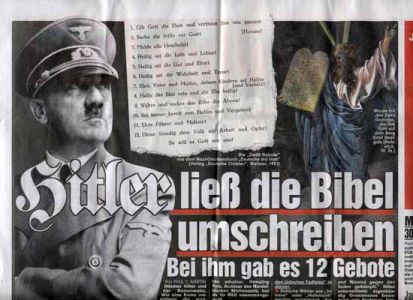
Hitler lügt wie gedruckt
Von wegen Schaftstiefelgrotesk – der Führer steht doch mehr auf Schwabacher Judenlettern, jedenfalls, wenn man der heutigen BILD glauben mag.
Ich finde diesen Deinen Beitrag eher fehl am Platze und überflüssig.
Solche (BILD-Zeitungs-)Beiträge ignoriert man, aber man wertet sie nicht auf, indem man sie zusätzlich irgendwo publiziert. Darüber hinaus sollte man solche antisemitischen Begriffe in Anführung zitieren "Schwabacher Judenlettern", sonst bekommt das noch, wie man im Schwabenland sagt, "Geschmäckle".
Das "Judenlettern" war ja wohl eher als Zitat gemeint (und lediglich nicht als solches gekennzeichnet), oder?
Die Bild belegt zumindest ihre typografische Unbedarftheit und ist damit ein weiterer Beleg für die These, dass gebrochene Schrift – egal welche – noch immer für einen Nazikontext gut ist, feine Unterschiede (Schwabacher oder Schaftstiefel) gehen da schon mal schnell unter.
Professoren sind auch nur Menschen! :lol:
Mein Ex-Chef ist zwar zugegebenermaßen ein Naturwissenschaftler und hat mit Typo und Layout nichts am Hut, aber trotzdem ist dieses Zitat bezüglich der FAZ doch sehr bezeichnend, was die generelle Wahrnehmung der gebrochenen Schriften durch selbst hochintelligenter Akademiker angeht. Er meinte zu mir: »Solange die FAZ diese Nazi-Schrift benutzt, lese ich sie nicht!« Da hilft auch der Normalschrifterlass nicht wirklich ...
Joh.. genau so hirnrissig wie Leute, die meinen Web-Auftritt in eine Braune Ecke stellen. Und daß auch noch in Schriftform. Das liest sich dann wie eine Einladung, ihnen mal aus pädagogischen Gründen über meinen Anwalt auf die Finger zu klopfen.
Aber gegen Ignoranz ist halt schwer anzukommen.
Übrigens handelt die Titelgeschichte des neuen SPIEGEL über "Der Deutschen Reich". <Ironie> Sicher auch alles verkappte Nazis dort beim Spiegel. <Ironie>
ist mein bäcker jetzt ein nazi oder doch ein jude?
nein, mein deutscher bäcker verwendet die fette fraktur als brotschrift.
Zu dem Beitrag, rein interessehalber, was war denn Hitlers zwoelftes Gebot?
"Du sollst nicht führen meinen Namen unnütz in Deiner Rede, um Aufmerksamkeit zu finden, wenn Du eigentlich nur jemanden suchst, der Dich bei Deinem Global-Dings-Projekt unterstützt."
an Georg: Hattest Du nicht mal so einen Link parat, der zu einer obskuren
Fraktursammlung fuehrte, wo man sich manches herunterladen konnte.
(War recht bunt und unuebersichtlich)
Oh ja. Der Timothy Leary der Fraktur-Schriften:
Harhar, der war richtig gut.